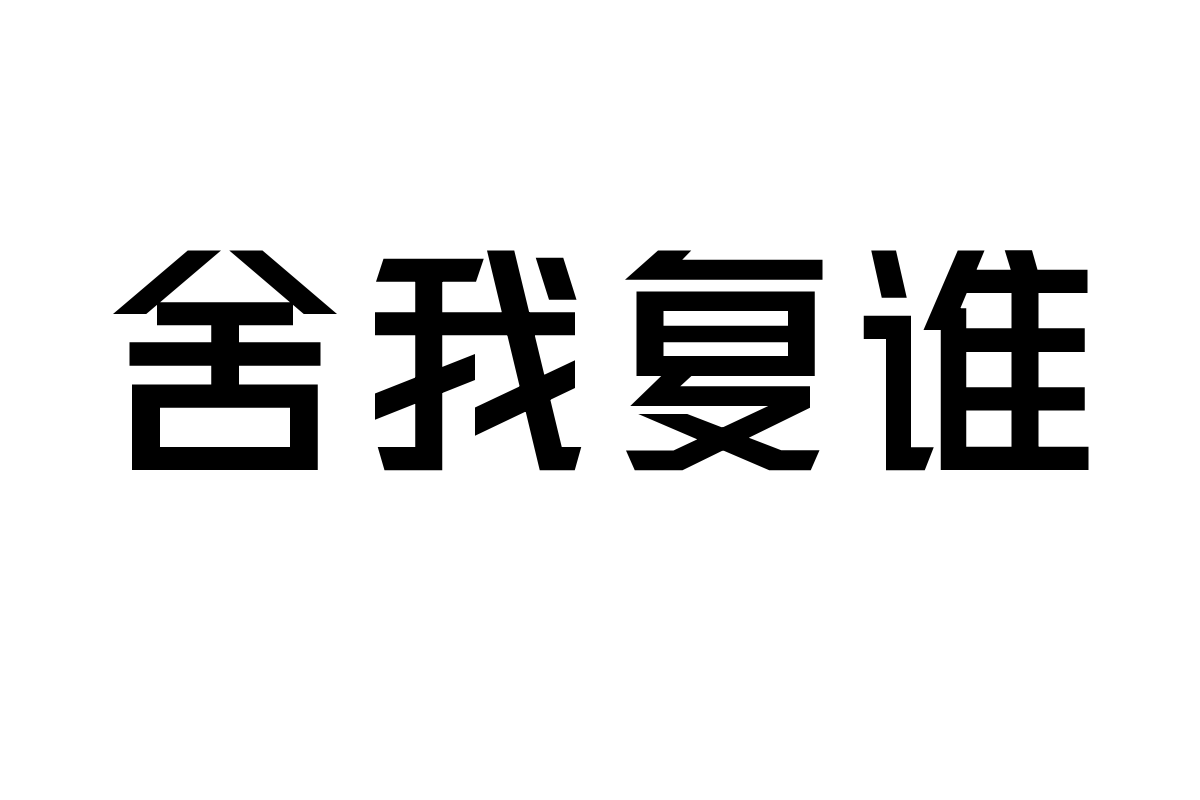
三极黑简体字体是一款具有独特设计特点的中文字体,它以其简洁、清晰和易读的特点而受到广泛欢迎。这款字体采用了传统的黑体结构,但进行了一些创新和调整,使其更符合现代审美和阅读习惯。
首先,三极黑简体字体的笔画粗细适中,既不过于粗犷也不过于细薄,这使得它在视觉上更加平衡和协调。其次,这款字体的字形结构紧凑,线条流畅,使得文字在阅读时更加清晰易懂。此外,三极黑简体字体还注重了细节的处理,如字间距、行间距等,都经过精心设计,使得整个字体看起来更加美观大方。
总的来说,三极黑简体字体是一款非常适合用于正式文件、商业广告、新闻报道等多种场合的中文字体。它的简洁、清晰和易读的特点,使得它在各种应用场景中都能够发挥出良好的效果。